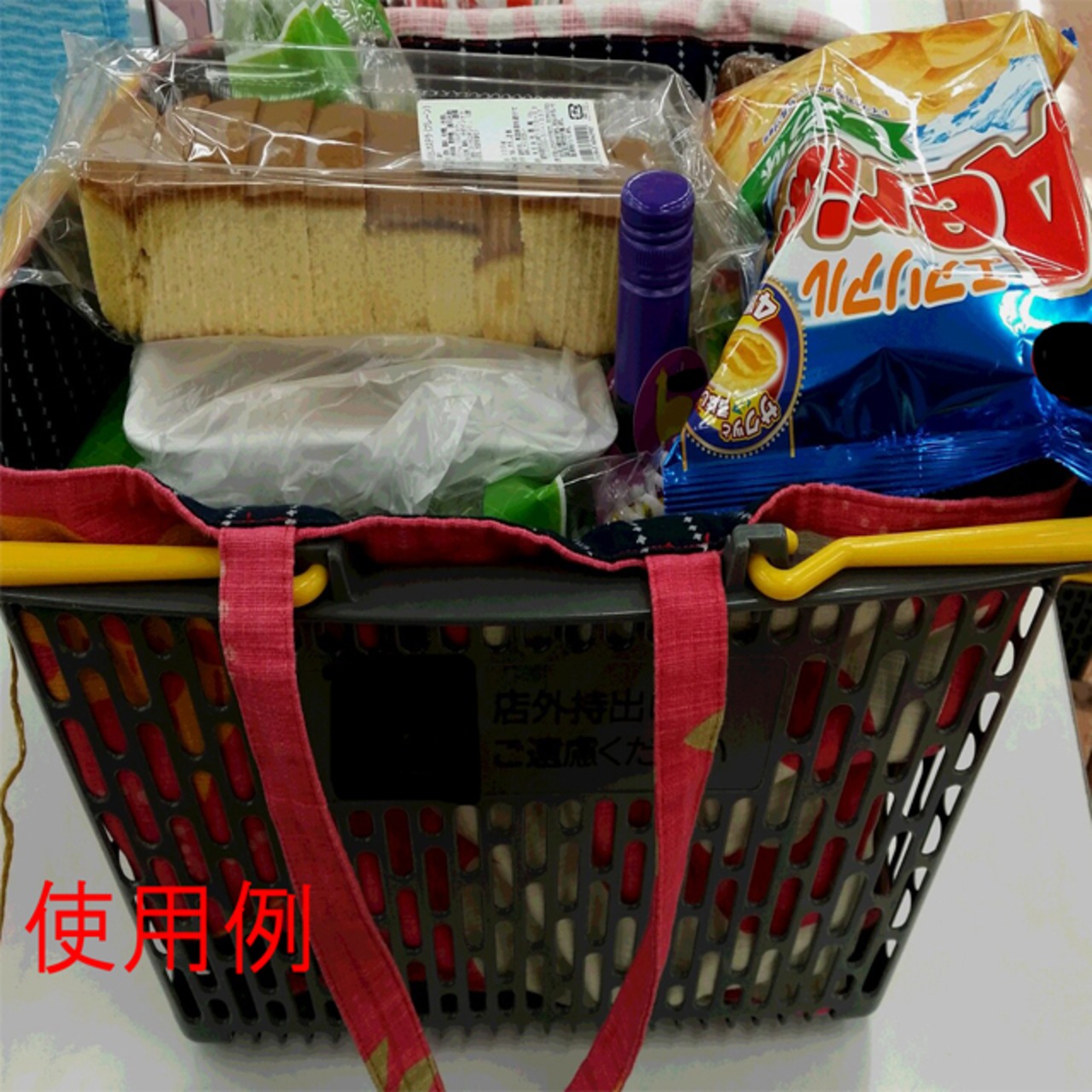
SmileレジかごバックNo13☆
Smileレジかごバック第13弾出来ました~♪
超cuteピンクとホワイトのストライプが初登場です( *´艸`)フフッ これからの季節にピッタリ☆
ゆるりが筆で書いた文字やイラストをシルクスクリーン印刷で仕上げたオリジナルの生地を使い,表地&裏地&カラー・・・同じ組み合わせは2度とない完全オリジナル♪
いつも使うものだからオシャレで個性的なものにこだわりたい!!
Smile少なめ・・・でもちゃんといますよ~~♪
毎日の買い物がウキウキになっちゃうかも・・・
お買い物精算時にレジかごにバックをセットすれば、詰め替える手間も省けキレイに入れてもらえてとっても便利!!(写真参考)
サイドに紐が付いているので大量の買い物でも横から物が落ちにくくなってます。
蓋付きだから、中身も見えにくい!
更に更に!使わないときはたたんでおいて置けるベルト付き♡
表地 綿50%&ポリエステル50% 裏地 綿100%
size タテ35×ヨコ21×高さ27 底タテ35×ヨコ18(全てcm)